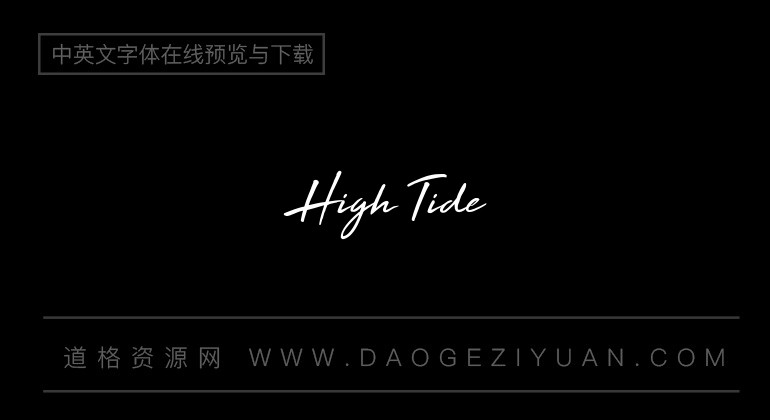
High Tide
High Tide 是一种漂亮的手写风格字体,由Jonathan S. Harris设计。这种字体具有轻快、自然和亲切的感觉,适合用于许多不同的项目和应用程序中。 High Tide 字体具有一些独特的特征,例如字母的笔画不是完美的直线,而是略微波动,这使得字母看起来更加生动和真实。此外,字母之间的间距也相对较小,这使得字体更加紧凑和流畅。 High Tide 字体包含大写字母、小写字母、数字和标点符号,可用于许多不同的设计项目,例如印刷品、海报、标志、网站、贺卡等等。如果你正在寻找一种优美、自然的手写风格字体,High Tide 可能是一个不错的选择。
High Tide是一款非常不错的手写艺术字体,具有很好的视觉感,适合于文化类的宣传设计、商业类品牌的广告和产品包装设计以及个性化文字排版等较多场景。